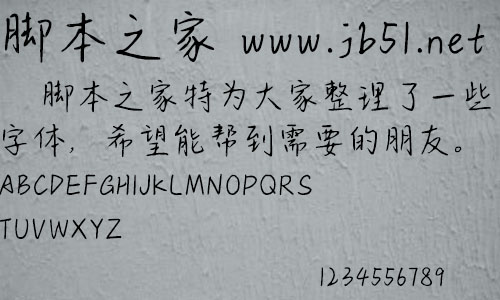
漢儀不對(duì)你撒謊簡(jiǎn)一款不錯(cuò)的藝術(shù)字體,由漢儀字庫(kù)出品,字體筆觸纖細(xì),書(shū)寫(xiě)流暢,具有很好的視覺(jué)感,適合應(yīng)用于藝術(shù)設(shè)計(jì)、平面宣傳設(shè)計(jì)、網(wǎng)頁(yè)設(shè)計(jì),書(shū)法字帖等領(lǐng)域,需要的朋友可以前來(lái)本站下載。